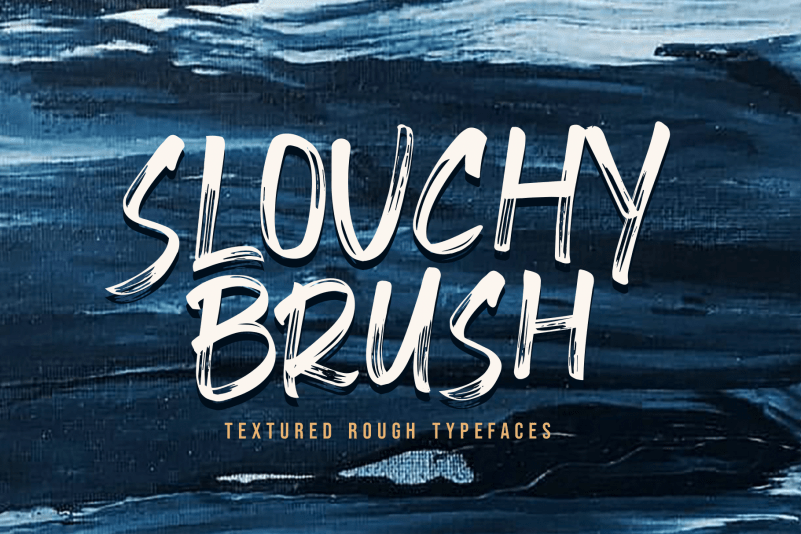
A fonte Slouchy Brush Font é uma nova opção no universo das fuentes brush. Ela traz um visual natural e casual com ares fortezinhos, apresentando traços que parecem escritos à mão, mas são realmente criados por computador. Este design foi pensado para combinar perfeitamente em diversas aplicações, como adesivos de propaganda, criação de logotipos, embalagens de produtos e até textos com estilos sólidos sobrepostos a qualquer fundo ou proposta. A fonte é uma mistura única de traços suaves e texturizados, que parecem ter sido formados ao ar livre, criando um resultado único e autêntico sem perder o controle. Com esta fonte da 50fox, você pode experimentar um novo e interessante modo de expressão visual em seus projetos.